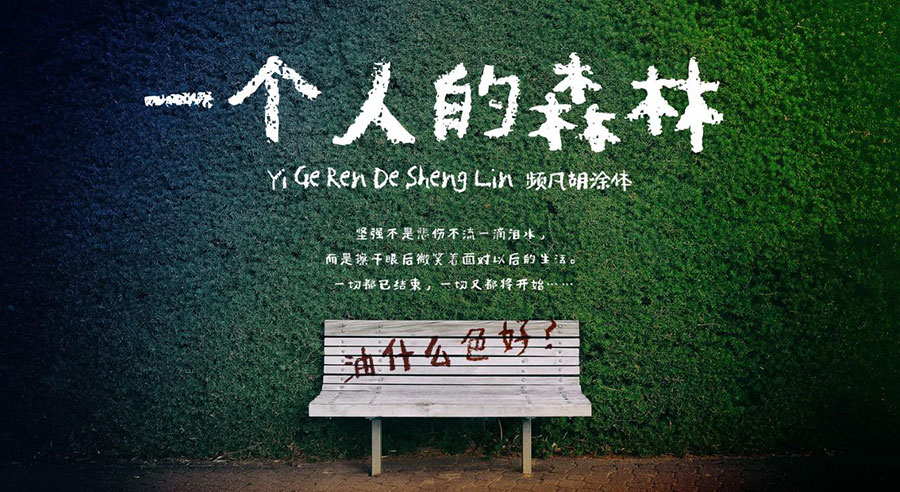
字體來源:給兒子生日製作畫面標題時,偶然發現一款日文字體,頻凡感覺非常適合。奈何整體完成度較低,只含括二千餘漢字,且多為日系繁體字形。字體應用後愈加喜歡,相遇即有緣,權當一份未來的生日禮物,遂產生增補衝動。字體命名來源於自己中年對“難得糊塗”的理解及字體塗鴉的本身。
增補目標:一、支持簡體中文編碼——現代漢語常用字表(3500字),另按字頻增加高頻漢字及符號。二、支持GB/T 2312 漢字表(6763字),滿足中文簡體需求;發佈1.0簡體正式版。三、酌情補充常用繁體中文字符,滿足國人中文簡繁基礎應用;發佈2.0簡繁正式版。
調整字形:原字隨性浪漫,字符大小不一,更有“逼真的筆跡感”;但因此使用性非常有限,字符堆疊難予辨認,尤其不適合文本。基於設計感與閱讀性的平衡,促進字體完成度,統一了字符寬高,逐字調整字符大小。同時,發現並修改原有日系字形,使其更加貼合簡體中文規範和習慣。
這是一款手寫字體,視覺上如同油漆/蠟筆在不平的表面塗抹,留下斑駁厚重的墨跡。粗糙中流露溫柔,歲月感不顯滄桑,純手工賦予的文藝氣質,推薦應用於動漫標題詩歌短文等場景。